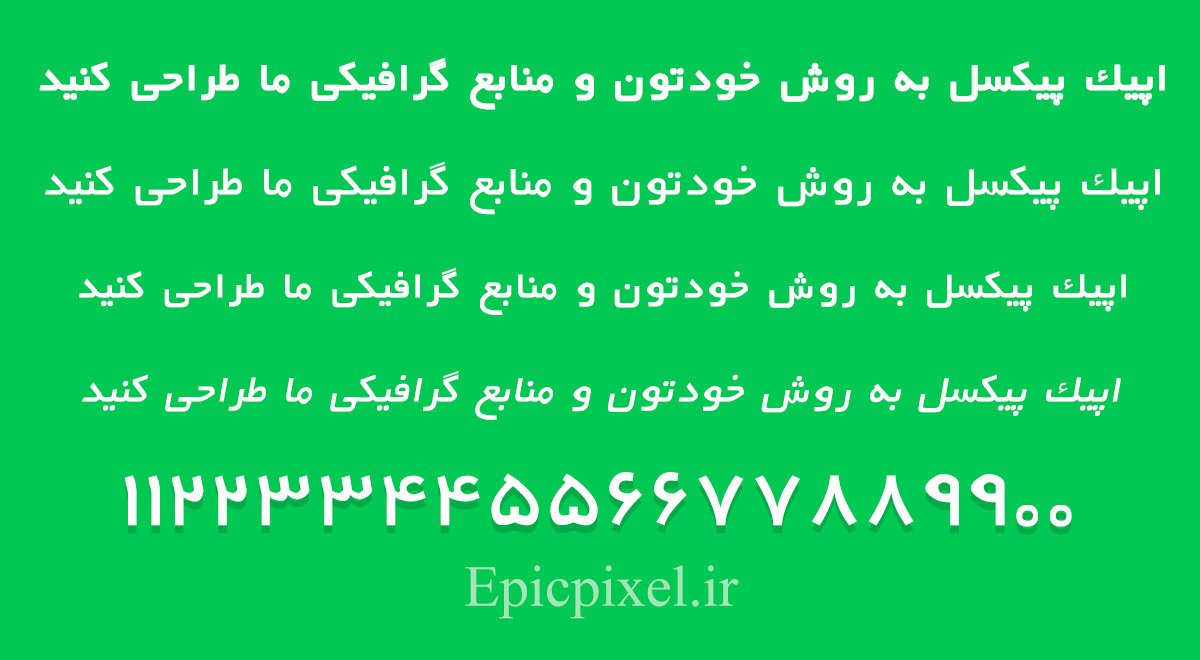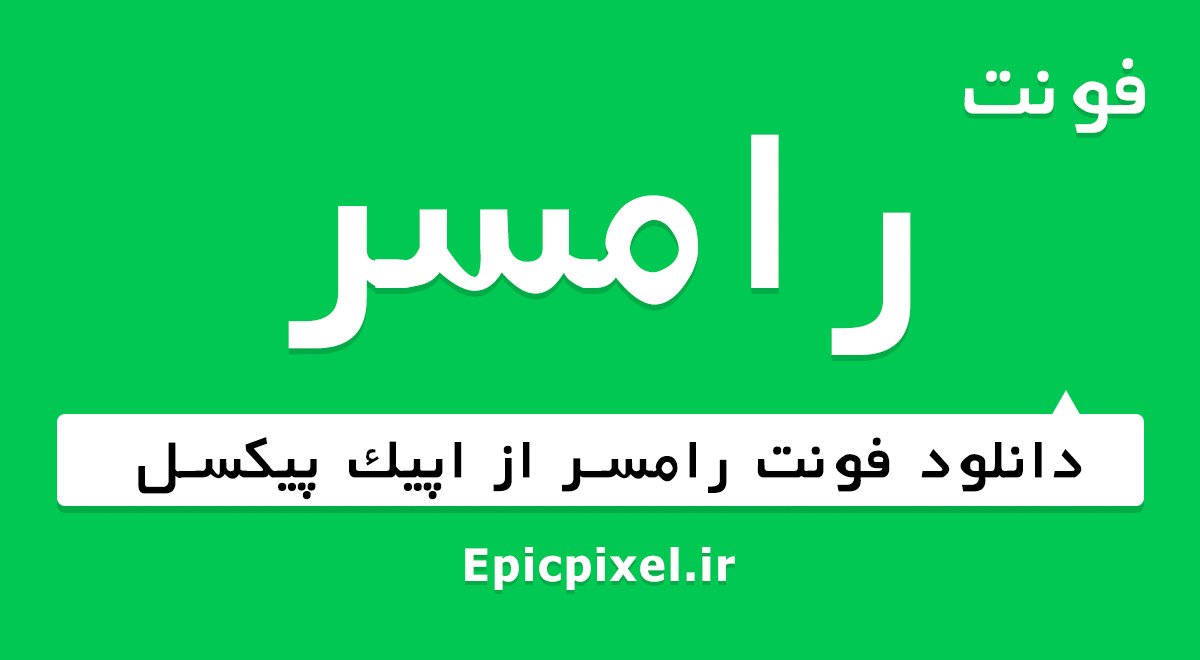
2 فونت رامسر فارسی
فونت رامسر فارسی، با طراحی خاص خود، ظاهری زیبا و خوانا به متون می بخشد. این فونت که به صورت رایگان در دسترس است، برای استفاده در انواع پروژه ها از جمله طراحی وبسایت، اسناد چاپی، و پروژه های گرافیکی مناسب است. یکی از ویژگی های برجسته این فونت، هماهنگی آن با زبان فارسی است؛ به طوری که حروف و اتصالات به شکلی طبیعی و روان نمایش داده می شوند و خوانایی متن را افزایش می دهند.
این فونت با داشتن وزن های مختلف، امکان ایجاد تنوع در طراحی را فراهم می کند. به این معنی که شما می توانید از وزن های مختلف آن برای عناوین، متن اصلی و سایر بخش های طراحی خود استفاده کنید و به این ترتیب، ساختاری بصری منسجم و جذاب ایجاد کنید. همچنین، فونت رامسر فارسی به خوبی در اندازه های مختلف نمایش داده می شود و چه در صفحات وب و چه در چاپ، کیفیت خود را حفظ می کند. این ویژگی به ویژه برای طراحانی که به دنبال فونتی هستند که در هر محیطی به خوبی عمل کند، بسیار مهم است.
البته باید به این نکته هم توجه داشت که فونت رامسر فارسی، مانند هر فونت دیگری، ممکن است برای همه سلیقه ها مناسب نباشد. برخی ممکن است طراحی آن را بیش از حد ساده یا کم تنوع بدانند. با این حال، رایگان بودن و خوانایی بالای آن، این فونت را به گزینه ای ارزشمند برای بسیاری از کاربران تبدیل کرده است. اگر به دنبال فونتی هستید که هم رایگان باشد، هم خوانایی بالایی داشته باشد و هم به خوبی با زبان فارسی سازگار باشد، فونت رامسر فارسی می تواند انتخاب مناسبی برای شما باشد. به خصوص برای کسانی که به دنبال فونتی با ظاهر کلاسیک و در عین حال مدرن هستند این فونت می تواند گزینه خوبی باشد.